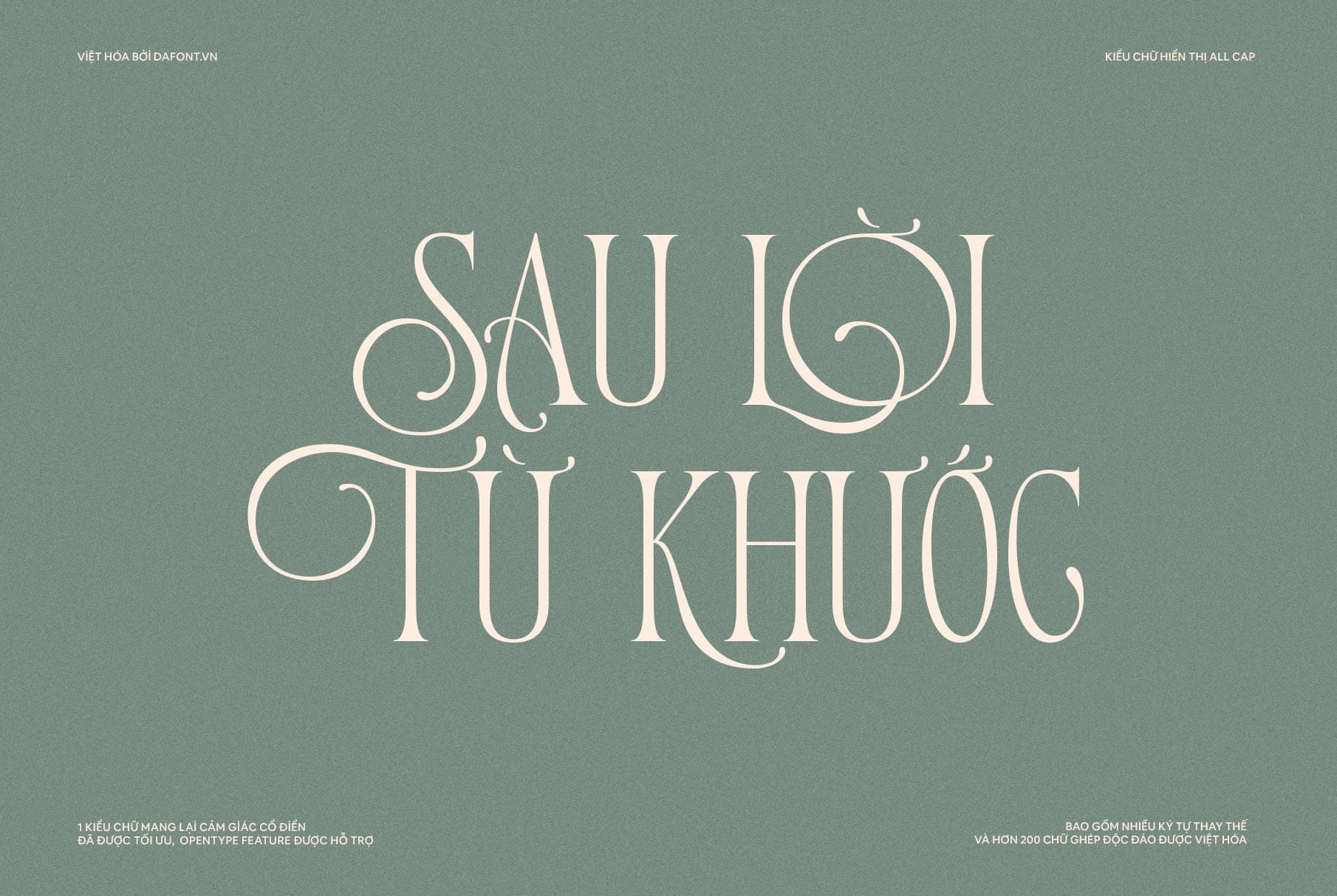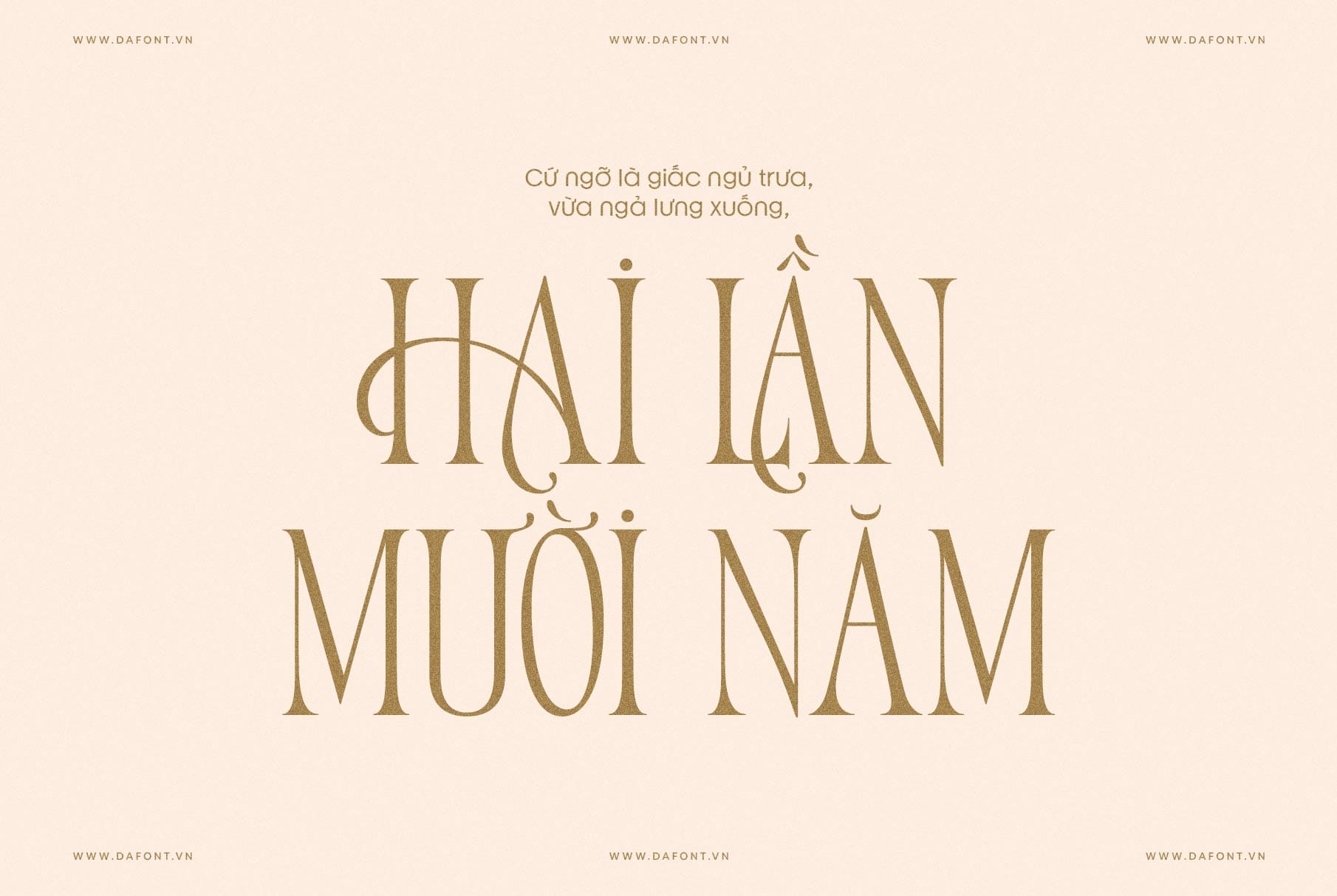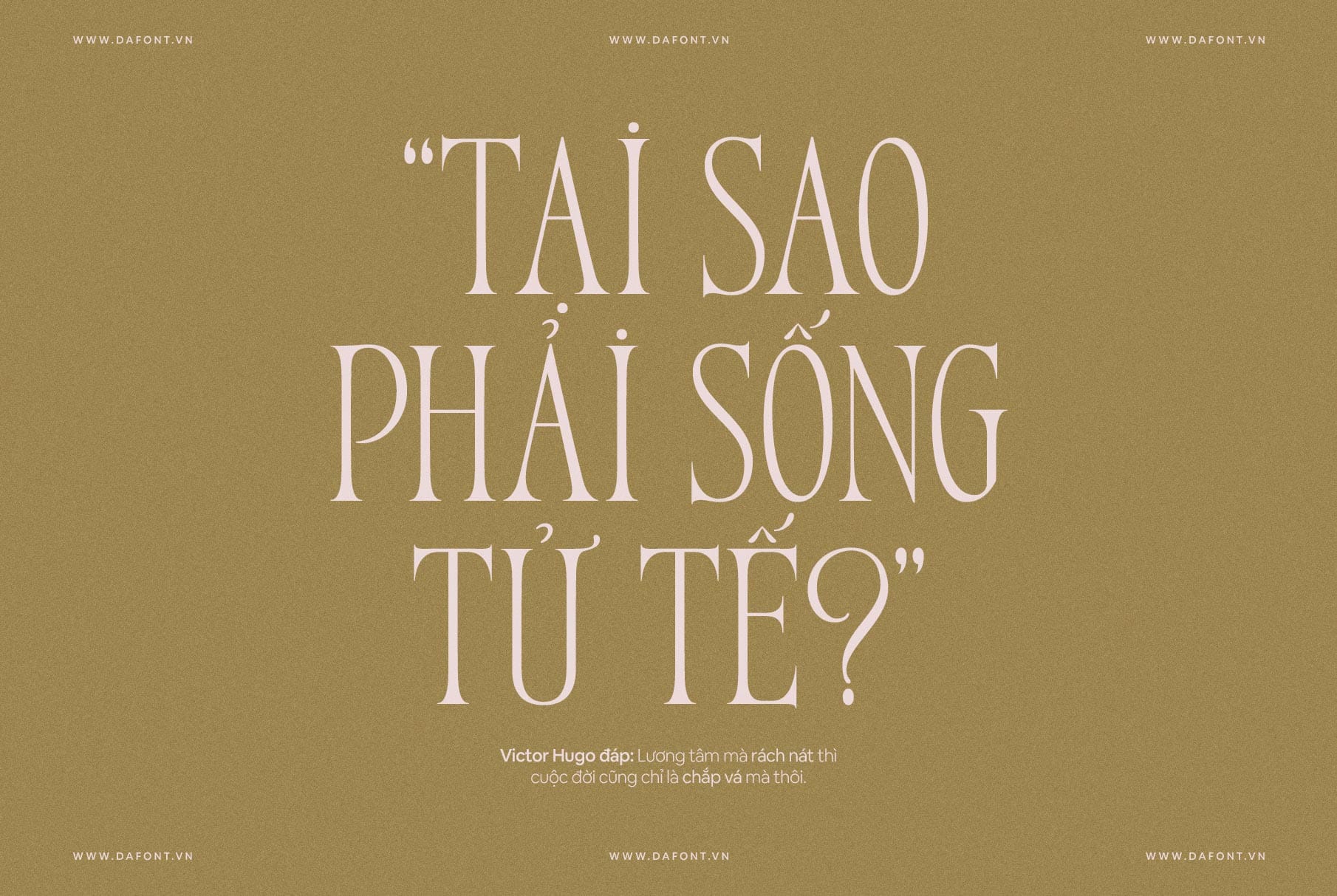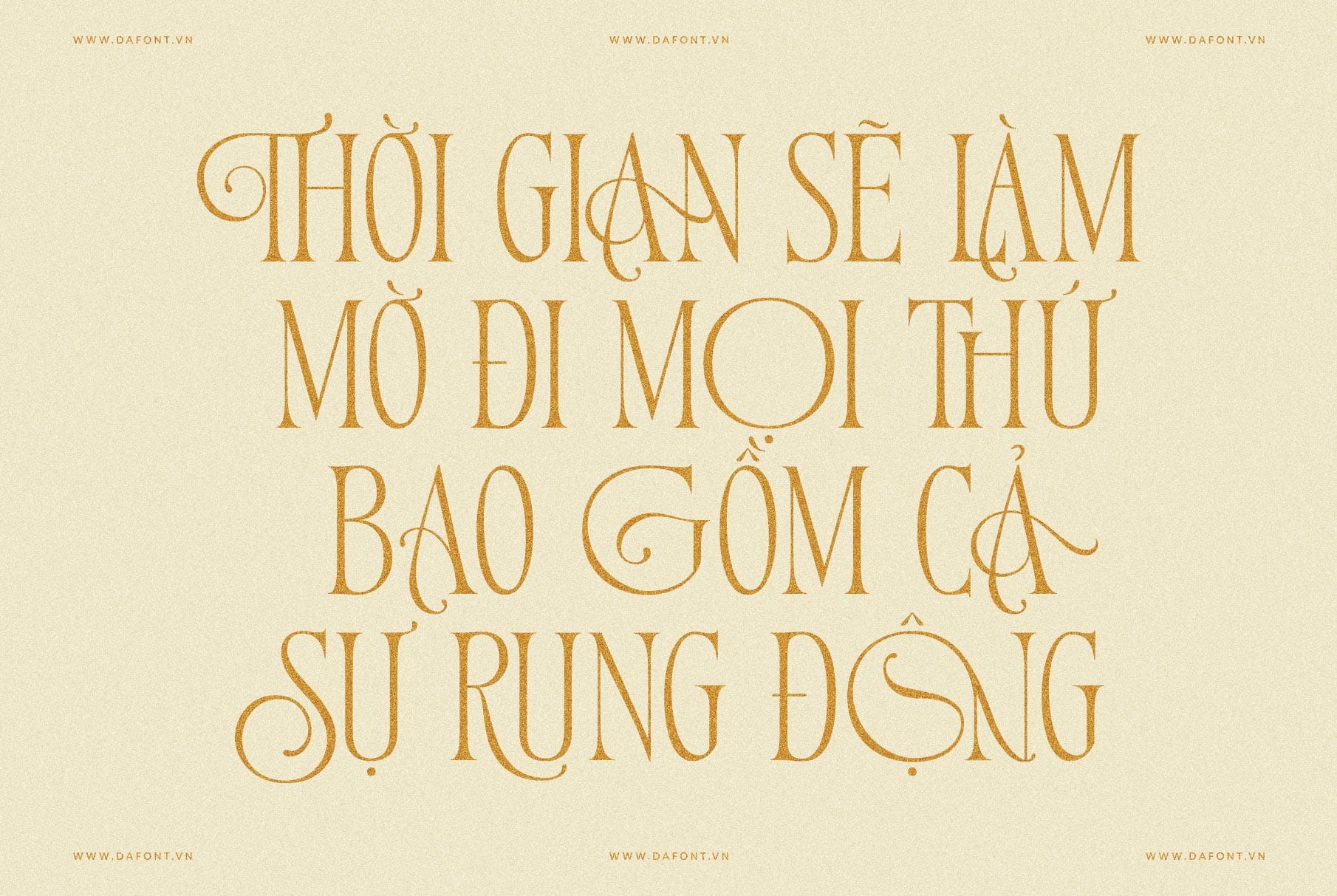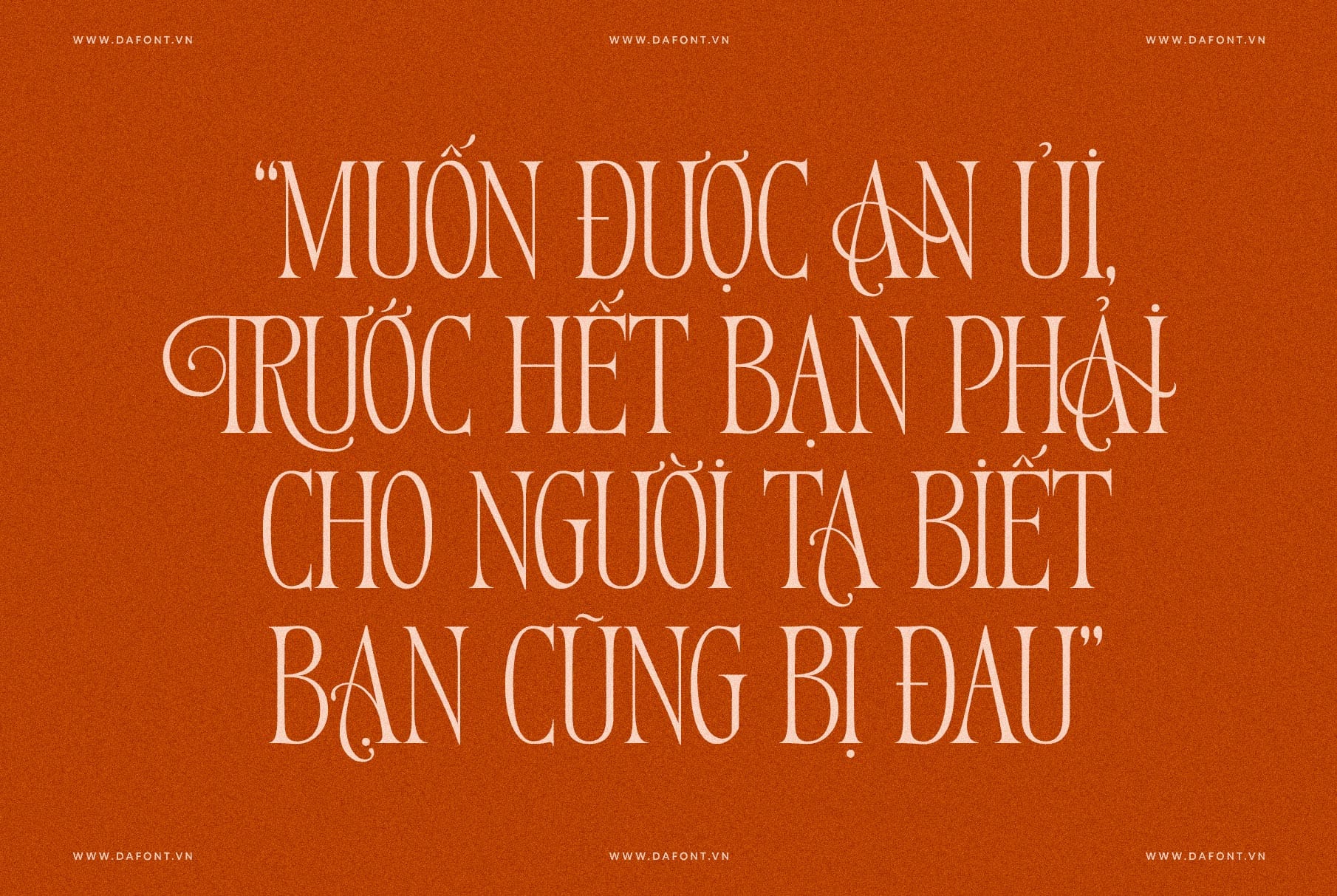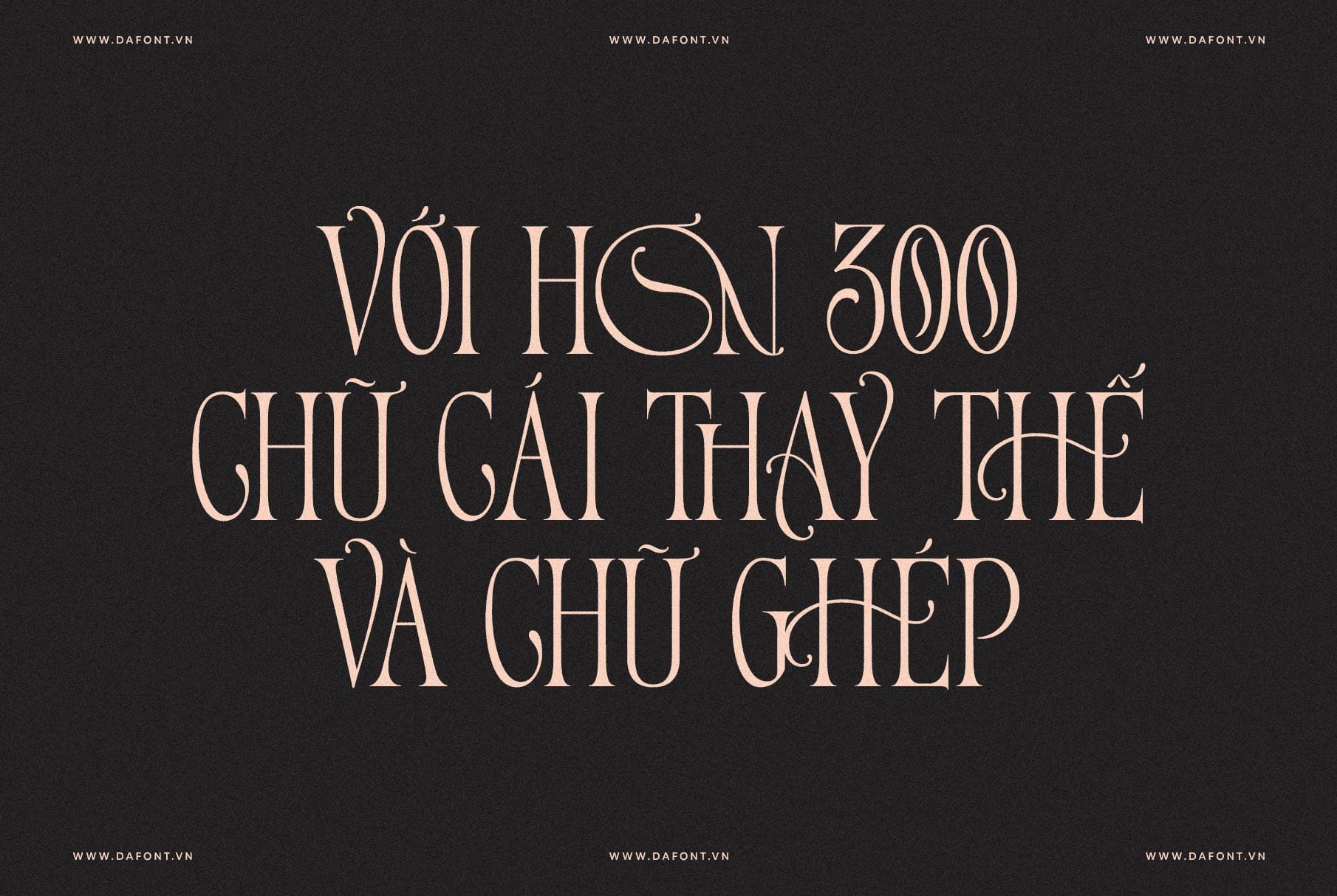
DFVN Tan – Variety là một font chữ hiển thị viết hoa toàn bộ (“all caps”), mang phong cách cổ điển và sang trọng. Font này là sự kết hợp hoàn hảo giữa tính thẩm mỹ và sự tinh tế, khiến nó trở thành một kiểu font độc đáo và phù hợp cho nhiều dự án thiết kế khác nhau.
DFVN Tan – Variety đem lại vẻ đẹp đặc trưng, đầy cuốn hút nhờ vào kiểu chữ viết hoa tỉ mỹ. Ngoài ra, font bao gồm nhiều ký tự thay thế và chữ ghép uốn lượn đẹp mắt giúp các thiết kế của bạn nổi bật hơn.
Điểm nhấn về font DFVN TAN – VARIETY
Tan Variety là một font chữ đặc biệt từ nhà thiết kế TanType, nổi tiếng với phong cách thiết kế thanh lịch, hiện đại và độc đáo. Dưới đây là những đặc điểm nổi bật của font:
- Thiết kế All Cap: Tan – Variety được thiết kế với tất cả chữ viết hoa, tạo nên sự đồng bộ và đồng nhất trong bất kỳ thiết kế nào.
- Ký tự thiết kế lạ mắt: Sự kết hợp giữa các đường nét đơn giản và chi tiết cầu kỳ tạo nên sự khác biệt, giúp Tan Variety nổi bật trong mọi thiết kế.
- Phong cách cổ điển: Với phong cách cổ điển, font này mang lại cảm giác thanh lịch và đẳng cấp, phù hợp với các dự án sang trọng và sáng tạo.
- Nhiều ký tự thay thế và chữ ghép độc đáo: Với hơn 300 chữ cái thay thế và chữ ghép được tối ưu và việt hóa đầy đủ mang đến nhiều khả năng sáng tạo hơn.
DFVN Tan – Variety phù hợp với nhiều loại dự án như:
- Thiết kế logo: Tính độc đáo và đồng nhất giúp font này nổi bật trên các logo thương hiệu.
- Biên tập tạp chí: Tan Variety font mang lại phong cách thanh lịch, rất phù hợp với các dự án in ấn.
- Thời trang: Được ứng dụng rộng rãi trong các bố cục sưu tập và bao bì sản phẩm cao cấp.
- Nhiều dự án thiết kế khác: Với vẻ ngoài cổ điển font này phù hợp cho nhiều dự án thiết kế khác như thiệp mời, poster, quảng cáo, trích dẫn…
DFVN Tan – Variety là sự lựa chọn hoàn hảo cho những ai muốn tìm kiếm một font chữ hiển thị đậm chất sang trọng và tinh tế. Dù bạn đang thiết kế logo, biên tập tạp chí hay lên ý tưởng cho một bố cục thời trang, Tan Variety sẽ là font chữ tuyệt vời giúp bạn thể hiện phong cách của mình.